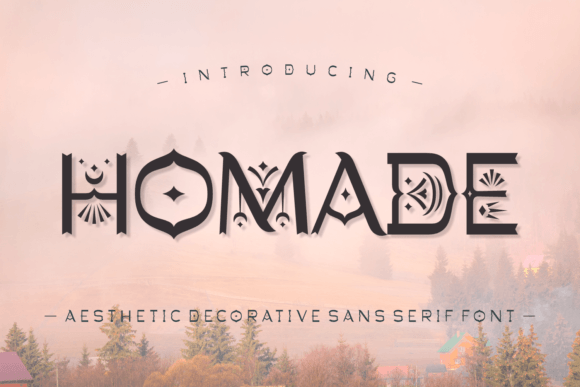
Homade
قد يكون العثور على عناصر التصميم المناسبة أمرًا صعبًا، ولكن Homade يقدم مجموعة استثنائية ترتقي بعملك على الفور.
سواء كنت تقوم بإنشاء منتجات الطباعة عند الطلب أو دعوات الزفاف أو رسومات وسائل التواصل الاجتماعي، فإن Homade هو الخيار المثالي.